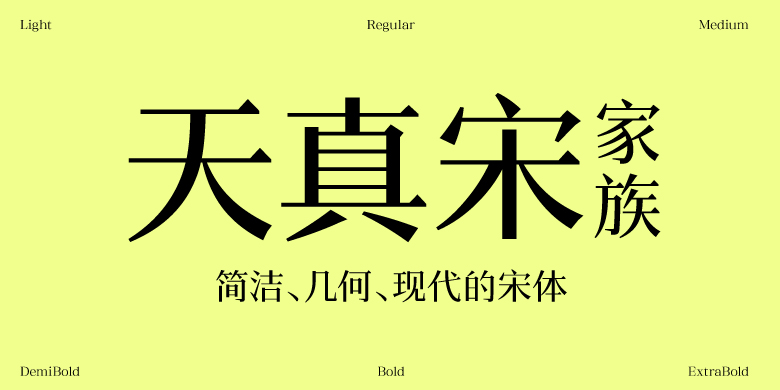
方正天真宋家族
方正天真宋家族,这款字体结构工整、笔画清晰,兼顾美观与易读性,适用于标题、正文、海报、包装、LOGO 等多种场景。字形优雅稳定,风格百搭耐看,适配日常排版与创意设计,让文字呈现更舒适、更具质感。方正天真宋家族一笔一画,皆是细节,以均衡的比例、流畅的线条打造舒适视觉体验,字形端正大气,风格简约现代。无论是商业设计、品牌宣传还是日常排版,都能轻松驾驭,让文字更有格调与力量。方正天真宋家族字体下载。
字体品牌: 方正字库设计师:税洋珊 字体分类:宋体 字体属性:精品字 字符集:大陆简体(GB2312-80) 发布时间: 2023
天真宋是一款简洁、几何、现代的宋体,骨架均匀、笔画极简,充满明快干净的少年气。这款字形是第十届方正奖专业组优秀奖的作品。